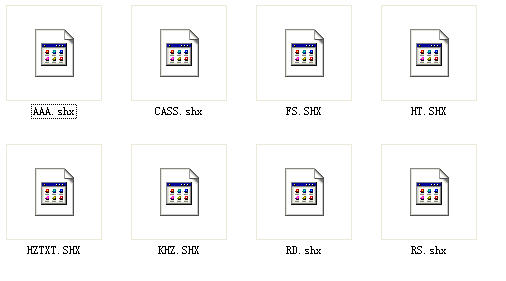
cad2007兼容字體
cad2007兼容字體是一類非常特殊的字體,該字體在生活中比較少見,一般只有在特殊的廣告宣傳圖上才會存在的,所以也就適合制作廣告圖片宣傳的朋友們使用,其字體也非常的具有特色,感興趣的朋友可以來綠色資源網(wǎng)進(jìn)行下載使用。
字體介紹
cad2007與其它制圖軟件字體兼容需要的字體
cad2007兼容字體,能夠讓cad2007與其它制圖軟件字體兼容。